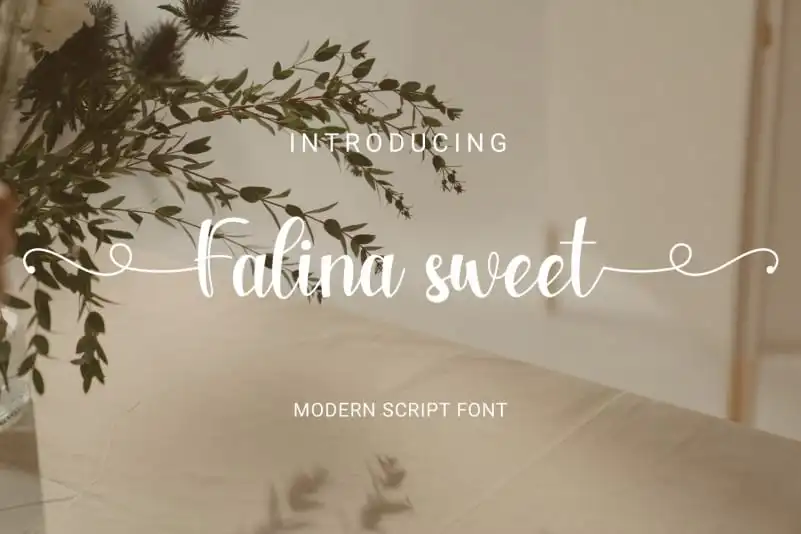
Falina sweet Calligraphy Font – Download Grátis
A Falina sweet Calligraphy Font é uma elegante fonte criada pela planetz studio, que oferece uma sensação autêntica e delicada de escrita à mão. Esta fonte não apenas adicionará um toque especial a seu design, mas também garantirá uma personalização única em cartões de aniversário, cartões de felicitações, convites de casamento, logotipos e até mesmo na criação de materiais empresariais. Seja ela usada em cartões de agradecimento para celebrar um evento significativo ou em um design de marca para dar seu trabalho uma cara personalizada, esta fonte é perfeita para qualquer projeto que você precise criar. Com Falina sweet Calligraphy Font, suas criações se tornam ainda mais únicas e memoráveis.